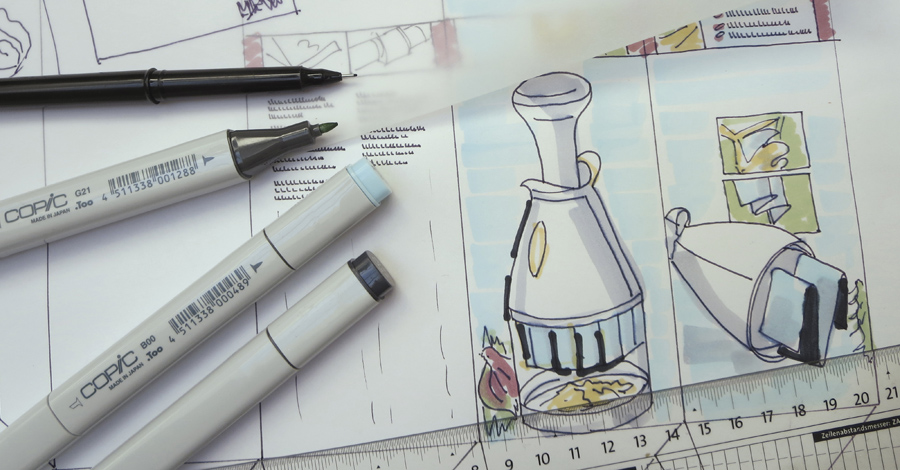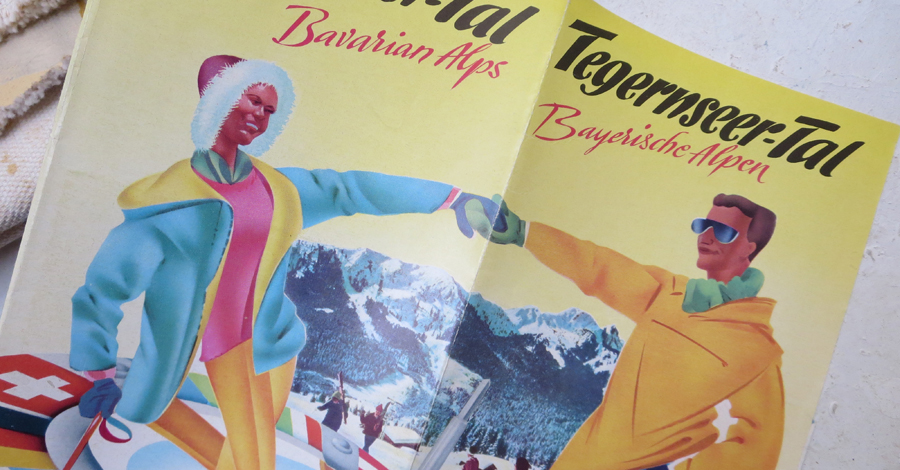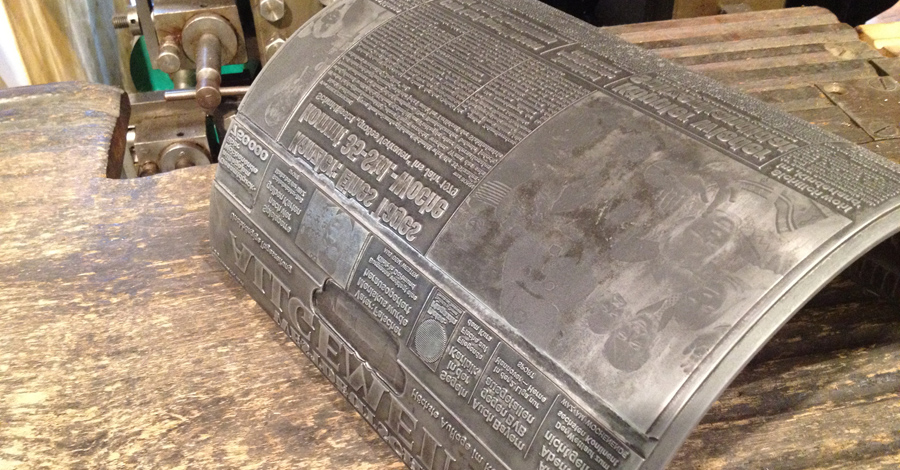
Typografie, Layout und Druck vor der Digitalisierung : War früher wirklich alles besser?
„Stimmt es, dass die typografische Qualität von Drucksachen in den 1960ern und 1970ern viel besser war als heute?“ Diese Frage stellen mir gelegentlich Kursteilnehmende. „Früher war alles besser“ höre ich auch oft die alten Kollegen sagen. Aber lässt sich das so einfach pauschalisieren?
Frage mit Folgen
Die Frage hat mich ganz schön nachdenklich gestimmt. In der Tat: Diese Vermutung und Aussage habe ich im Verlauf meines langen und aktiven Berufslebens schon x-mal zu hören bekommen. Ich konstatiere: Vor über 40 Jahren begann ich meine Ausbildung als Schriftsetzer im Bleisatz in einem grafischen Großbetrieb, in dem vom Akzidenzsatz bis zur Tageszeitung alles erstellt wurde. Heute coache ich überwiegend Grafik- und Kommunikationsdesigner sowie Mediengestalter meist in Unternehmen und direkt zu spezifischen Themen ihres Arbeitsalltags .
Vom Bleisatz zur Typografie im Responsive Web Design
Ein paar Zwischenstationen meiner Karriere: Bleisatz im Handsatz für anspruchsvolle Akzidenzdrucksachen, Maschinensatz im Linotype-Verfahren für Massendrucksachen der Buch-, Zeitungs- und Zeitschriftenproduktion. Die Umstellung auf Fotosatz: Diatype, Staromat Titelsatz und Filmmontage für den Offset-Druck. Später Klebeumbruch aus Papierabzügen, Reinzeichenmontagen auf Karton mit der Stahlschiene, Positiv-Retuschen mit Pinsel und Rapidograf. Noch später das Schriften rubbeln mit Letraset und Skalpell, Copic-Marker, Layoutpapier, Bildplatte, Overheadfolien und Diktafon, die uns beim Präsentieren von Werbestrategien unterstützen sollten. Unabhängig davon, ob Sie mit diesen Begriffen etwas anfangen können: Sie sehen, ich habe in meinem Berufsleben das Kommen und Gehen vieler „neuer“ Techniken miterlebt.
Mit Blei ausgegossene Druckform aus den 70ern – TypeSCHOOL Buchdruck Bleisatz
Schwere Sache aus den 1970ern: eine rundgebogene Mater und mit Blei ausgegossene Druckform für den Rotationshochdruck einer Tageszeitung. Die Headline lautet: „Kanzler: Eines Tages kommt 35-Stunden-Woche.“
Wandel heißt Entwicklung
Der Wandel von Produktionstechnologien in der visuellen Kommunikation bedeutet ständige Veränderung. Nicht jede neue Technik ist schlechter als die alte, aber auch nicht jede alte Technik besser als die neue. Heute genießen wir einen Komfort, der mit der früheren Arbeit als Bleisetzer und Buchdrucker nicht mehr zu vergleichen ist. Und um ehrlich zu sein: Ich möchte heute nicht mehr täglich acht Stunden lang mit Winkelhaken und Setzkasten arbeiten, auch wenn ich nach wie vor große Begeisterung für das Traditionshandwerk empfinde und gelegentlich sogar noch Workshops zu Bleisatz gebe.
Layouttechnik mit Copy-Markern – TypeSCHOOL Typografie Layout Kommunikationsdesign
Flotte Sache ohne Computer und Digitalkamera: Layouttechnik mit Copic-Markern auf Layoutpapier, wie sie bis Ende der 1980er-Jahre üblich war.
Beispiele mit Tief- und Abgang
Um die Frage nach der Qualität zu beantworten und um zu klären, ob früher wirklich alles besser war, habe ich mich in meiner umfangreichen Sammlung von historischen Drucksachen umgesehen. Einige davon stammen aus der Zeit, als Handsatz, Maschinensatz und Buchdruck noch Alltag waren; Andere aus der Zeit, als ein wachsendes Konsumverhalten die Nachfrage nach Kommunikationsdesign rasant erhöhte und sich ein technischer Wandel vollzog. Die folgenden Galerien zeigen Druckbeispiele aus diesen beiden „Druckepochen“, dem Akzidenzsatz und der Industrieproduktion.
4-Farb-Prospekt im Buchdruck aus den 60ern – Typeschool Layout Typografie Kommunikationsdesign
Erstaunlicher Kunstlauf: hochwertiger 4-Farb-Prospekt im Buchdruck gedruckt, Anfang der 1960er.
Wenn Sie mich fragen, sehe ich anhand der Druckbeispiele keinesfalls die Aussage bestätigt, dass Schrift-, Layout- und Druckqualität früher grundsätzlich besser waren. Wie in allen anderen Branchen gibt es jedoch auch im Kommunikationsdesign in allen Epochen weiße und schwarze Schafe. Aber urteilen Sie am besten selbst …
Druckbeispiele aus dem Akzidenzsatz und dem Maschinensatz in der Industrieproduktion aus meiner umfangreichen Sammlung zu Druckobjekten aus den 1950er bis 1970er Jahren
Die folgenden Bildbeispiele entstammen meiner umfangreichen Sammlung von original Drucksachen, die ich vor allem in der Zeit meiner Ausbildung gesammelt habe. Vieles wurde mir von Freunden und Liebhabern „bibliophiler Kunst“ zu treuen Händen übereignet, manches konnte ich bei Wohnungsräumungen vor dem Container retten.
Beispiele aus dem Akzidenzsatz
(Drucksachen in kleiner Auflage, die meist im Handsatz gesetzt und im Buchdruck mit dem Heidelberger Tiegel gedruckt wurden:
Liebevoll: Kalendersprüche im Handsatz mit Vignetten und 2. Druckform in Farbe.
Frech: Eigenwerbung einer Werbeagentur.
Umsteigen aufs Auto: liebevolle Illustrationen und schöner Satz auf Aquarellkarton gedruckt.
Verführerisch: Visitenkarte eines Modesalons in Basel.
So schön kann Weihnachten sein: liebevoll gesetzte Grußkarte im Handsatz, gesetzt mit Lenolschnitt.
DAS Ereignis im Frankfurter Zoo: Ankündigung einer neuen Löwenfamilie im modernen Schriftsatz.
Messe-Flyer: einfach nur schöner Satz.
Einladung zur Vernissage: klassisch, rechtsbündig, Helvetica – was will man mehr?
Wolf im Schafspelz: die Bleisatzschrift „Zebra“ mit Grauwirkung durch Schraffur.
Penetrant: Unterstreichung des Unternehmensnamens in den CI-Farben als typografische Auszeichnungsform.
1
Beispiele in großen Druckauflagen
(Drucksachen, die meist in Graphischen Großbetrieben im Maschinensatz gesetzt, im Buchdruck auf modernen Zylinderpressen gedruckt und in Buchbindereien weiterverarbeitet wurden:
Zieht wie Hechtsuppe: endlos lange Textzeilen – dafür schöner anaxialer Zeilenfall. Man beachte die moderne Kleinschreibung in der Headline.
Wohnidee mit Schock fürs Leben: vierfarbige Buchdruck-Klischees werben für Gelsenkirchener Barock.
Zeigen, wie‘s geht: Mit Tachoscheibe auf Deutschlands Straßen unterwegs ...
Auf den Arm genommen und kopflos: Maschinensatz mit Blocksatz und idealen Lücken zum rückwärts Einparken.
Bittere Pille: Antibiotica-Werbung mit flimmernder Schriftlinie und kariösem Flattersatz.
Eco-Design á la 1960er: Malermeister-Müller-Prospekt mit Farbkarte und gleichzeitigem Mehrwert als Luftfächer.
Buchproduktion: Monotype-Satz kombiniert mit Titel und Initial im Handsatz gesetzt.
Immer wieder übersichtlich: Fahrplan der Deutschen Bundesbahn mit Tabellen im Maschinensatz.
Werkstatt-Mailing: gewagte Schriftmischung mit Bildklischees ...
... und aufwändiger Stanzung mit buchbinderischem Falz.
Dieses Mailing will sagen: Ich saufe Superbenzin.
Schräge Sache: Schreibmaschinen-Mailing mit schlechtem Flattersatz.